使用字体:理杏黑简系列
使用位置:品牌手册封面、内页
为迎合全世界的医疗需求,在全球范围展开事业的制药企业,协和发酵KIRIN发布的品牌手册的封面与全部内页使用了理杏黑简字体,通过理杏黑简字体营造的简洁温和的氛围向全世界传达企业描绘的未来蓝图与理想。
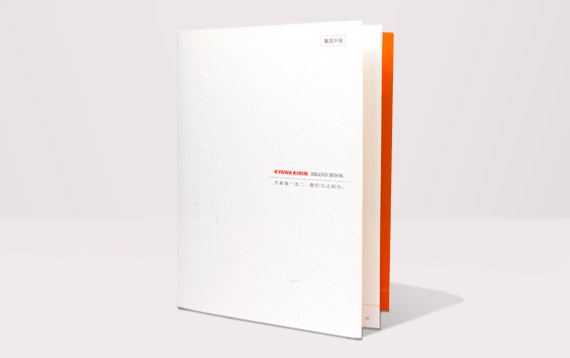
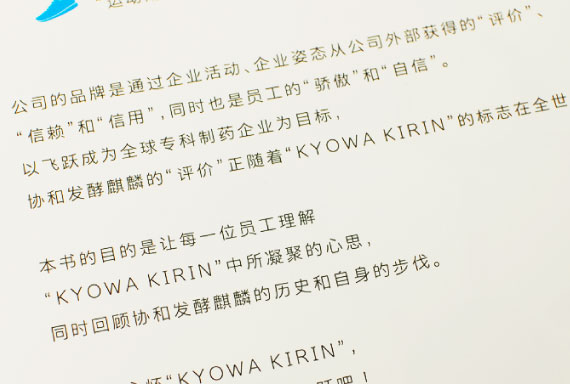
理杏黑简的7种粗细类型,满足各种排版设计需求。易于阅读、均衡的设计,创造唯美空间。简洁干练的字体中,传达最真挚的讯息。